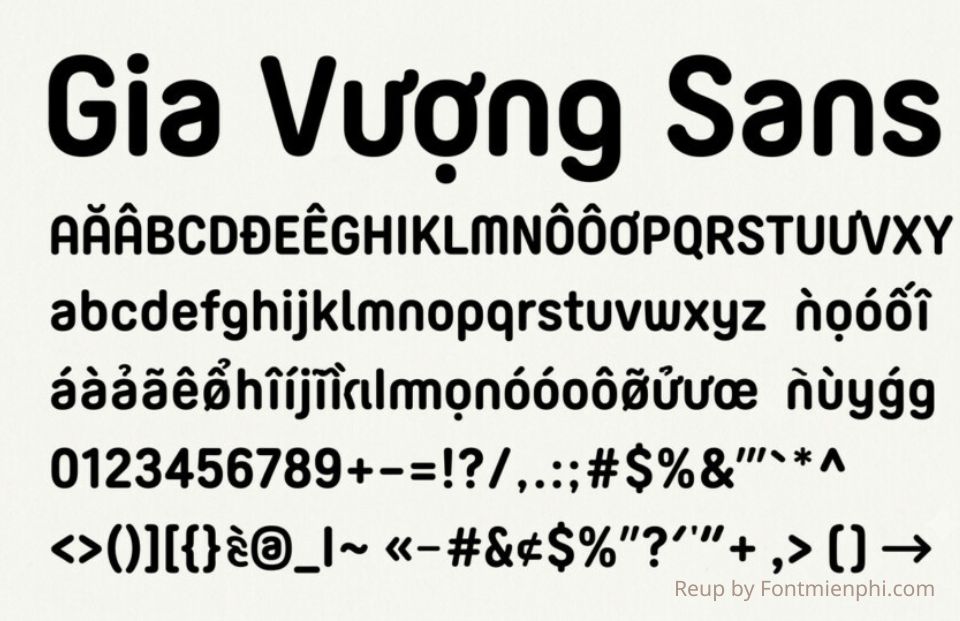
Font Gia Vượng Sans : Lựa Chọn Hoàn Hảo Cho Thiết Kế Hiện Đại
Font Gia Vượng Sans: Lựa Chọn Hoàn Hảo Cho Thiết Kế Hiện Đại
Trong thế giới thiết kế đồ họa và nghệ thuật chữ (typography), việc lựa chọn một phông chữ phù hợp quyết định đến 50% sự thành công của một ấn phẩm. Thời gian gần đây, Font Gia Vượng Sans đang trở thành cái tên được nhiều Designer săn đón. Với đường nét thanh thoát, hiện đại và khả năng hỗ trợ tiếng Việt tuyệt vời, đây chính là “mảnh ghép” hoàn hảo cho các dự án từ nhận diện thương hiệu đến thiết kế UI/UX.
Vậy điều gì làm nên sức hút của kiểu chữ này? Hãy cùng tìm hiểu chi tiết qua bài viết dưới đây.
Nguồn Gốc Và Đặc Điểm Nổi Bật Của Font Gia Vượng Sans
Gia Vượng Sans thuộc họ phông chữ Sans-serif (không chân), được thiết kế với mục tiêu mang lại sự rõ ràng, dễ đọc nhưng vẫn giữ được nét tinh tế, sang trọng. Khác với các dòng phông chữ cổ điển, Gia Vượng Sans tối giản hóa các đường nét thừa, tập trung vào cấu trúc hình học cân đối.
1. Thiết kế Sans-serif tối giản và tinh tế
Điểm nhấn lớn nhất của phông chữ này chính là sự gọn gàng. Các con chữ được thiết kế với tỷ lệ x-height (chiều cao của các chữ cái thường) hợp lý, giúp văn bản dù ở kích thước nhỏ vẫn cực kỳ dễ đọc.
2. Hỗ trợ tiếng Việt trọn vẹn (Bản Việt hóa chuẩn)
Một trong những nỗi lo lớn nhất của các Designer Việt Nam là tình trạng lỗi dấu (kerning lỗi, dấu bị lệch) khi sử dụng font nước ngoài. Font Gia Vượng Sans đã được xử lý dấu tiếng Việt vô cùng tỉ mỉ. Các dấu thanh (sắc, huyền, hỏi, ngã, nặng) được đặt ở vị trí cân đối, không bị chèn ép vào các ký tự chính.
3. Tính đa dụng với nhiều độ dày (Weights) khác nhau
Để phục vụ cho đa dạng mục đích thiết kế, bộ font này thường đi kèm với nhiều phiên bản độ dày như:
• Light / Thin: Phù hợp cho các đoạn văn bản dài, thanh thoát.
• Regular: Lựa chọn tiêu chuẩn cho nội dung website, bài viết.
• Bold / Extra Bold: Hoàn hảo để nhấn mạnh tiêu đề, thiết kế logo hoặc banner quảng cáo.
Ứng Dụng Thực Tế Của Gia Vượng Sans Trong Thiết Kế
Với tính thẩm mỹ cao và sự trung tính, phông chữ này có thể được ứng dụng linh hoạt trong rất nhiều lĩnh vực:
Thiết kế nhận diện thương hiệu (Branding)
Sự hiện đại của dòng Sans-serif luôn là lựa chọn hàng đầu cho các doanh nghiệp công nghệ, thời trang, kiến trúc hoặc F&B muốn hướng tới hình ảnh trẻ trung, chuyên nghiệp. Sử dụng Gia Vượng Sans làm logotype hoặc phông chữ chủ đạo trong Brand Guidelines sẽ tạo ra sự nhất quán và đáng tin cậy.
Thiết kế Giao diện người dùng (UI/UX Design)
Trên môi trường kỹ thuật số (màn hình máy tính, điện thoại), khả năng hiển thị rõ nét là yếu tố sống còn. Gia Vượng Sans đáp ứng xuất sắc tiêu chí này, giúp nâng cao trải nghiệm đọc của người dùng trên các website và ứng dụng di động.
Ấn phẩm truyền thông và in ấn
Từ poster, standee, tờ rơi cho đến các bài đăng trên mạng xã hội (Facebook, Instagram), font chữ này mang lại cảm giác dễ chịu, giúp thông điệp truyền tải đến khách hàng một cách trực diện và hiệu quả nhất.
• Đừng lạm dụng quá nhiều Font: Chỉ nên kết hợp Gia Vượng Sans với tối đa 1-2 phông chữ khác (thường là một font có chân – Serif hoặc font viết tay – Script) để tạo độ tương phản, tránh làm rối mắt người xem.
Tổng Kết
Nhìn chung, Font Gia Vượng Sans là một tài sản quý giá trong “kho vũ khí” của bất kỳ nhà thiết kế nào. Sự kết hợp giữa tính hiện đại, cấu trúc hình học chuẩn xác và sự tương thích hoàn hảo với tiếng Việt giúp phông chữ này tự tin chinh phục mọi phong cách thiết kế.